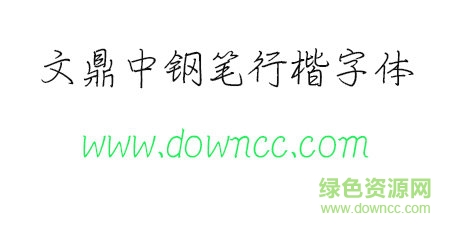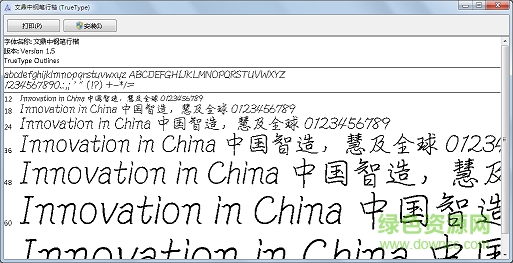
文鼎中鋼筆行楷是一款簡體字體。小編看見不少朋友在找文鼎中鋼筆行楷繁體,很可惜的告訴大家,只有簡體,沒有繁體,但是其字體設(shè)計還是非常具有特色亮點的,應(yīng)用的范圍也比較廣泛,需要的朋友可以來綠色資源網(wǎng)下載使用哦。
文鼎中鋼筆行楷,即簡約而不簡單,線條收筆處多以喇叭狀收尾,結(jié)構(gòu)經(jīng)典內(nèi)斂外擴重心微向上移,章法明朗流暢。文鼎中鋼筆行楷,端莊簡約,筆畫上處理精致得當(dāng)。結(jié)構(gòu)上分配塊面合理,字與字間的距離分配閱讀舒適爽朗。尤其在手機等移動小屏幕上顯示更是簡約極致的體現(xiàn)線條美。